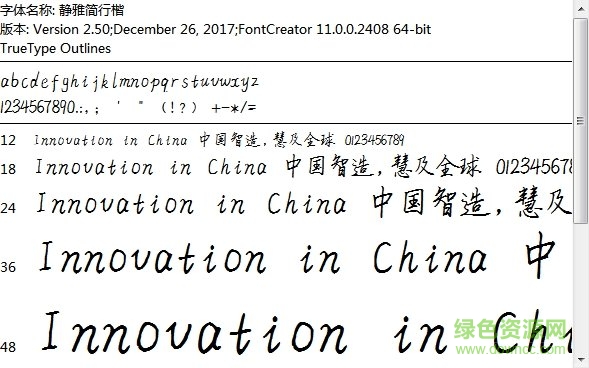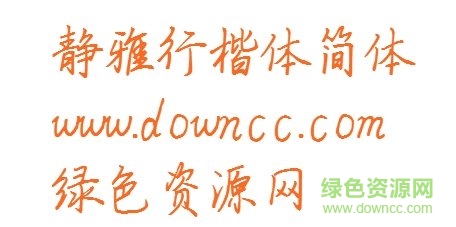
靜雅簡行楷書字體是一款運(yùn)筆細(xì)膩、章法鮮明的行楷字體,給人十分悅目的視覺呈現(xiàn),讓文字更加質(zhì)樸生動,
靜以修身,雅人深致——靜雅簡行楷。換一種字體,換一種心情!本字庫是在國家標(biāo)準(zhǔn)簡體字庫GB2312所包含6763漢字的基礎(chǔ)上,又增加了近200常用字,已經(jīng)覆蓋了大陸99.75%的漢字使用頻率,足以滿足日常需求。
靜雅簡行楷體有一股鋼筆字體的凌厲張揚(yáng)之美,用筆流暢、連貫從容,無凌亂潦草之象,可以廣泛運(yùn)用在藝術(shù)策劃、海報(bào)創(chuàng)意、平面設(shè)計(jì)等場合!